フォント名を教えてください
『わけないじゃん」と『Responsibility(責任)』のフォント名がわからないので、教えてください。
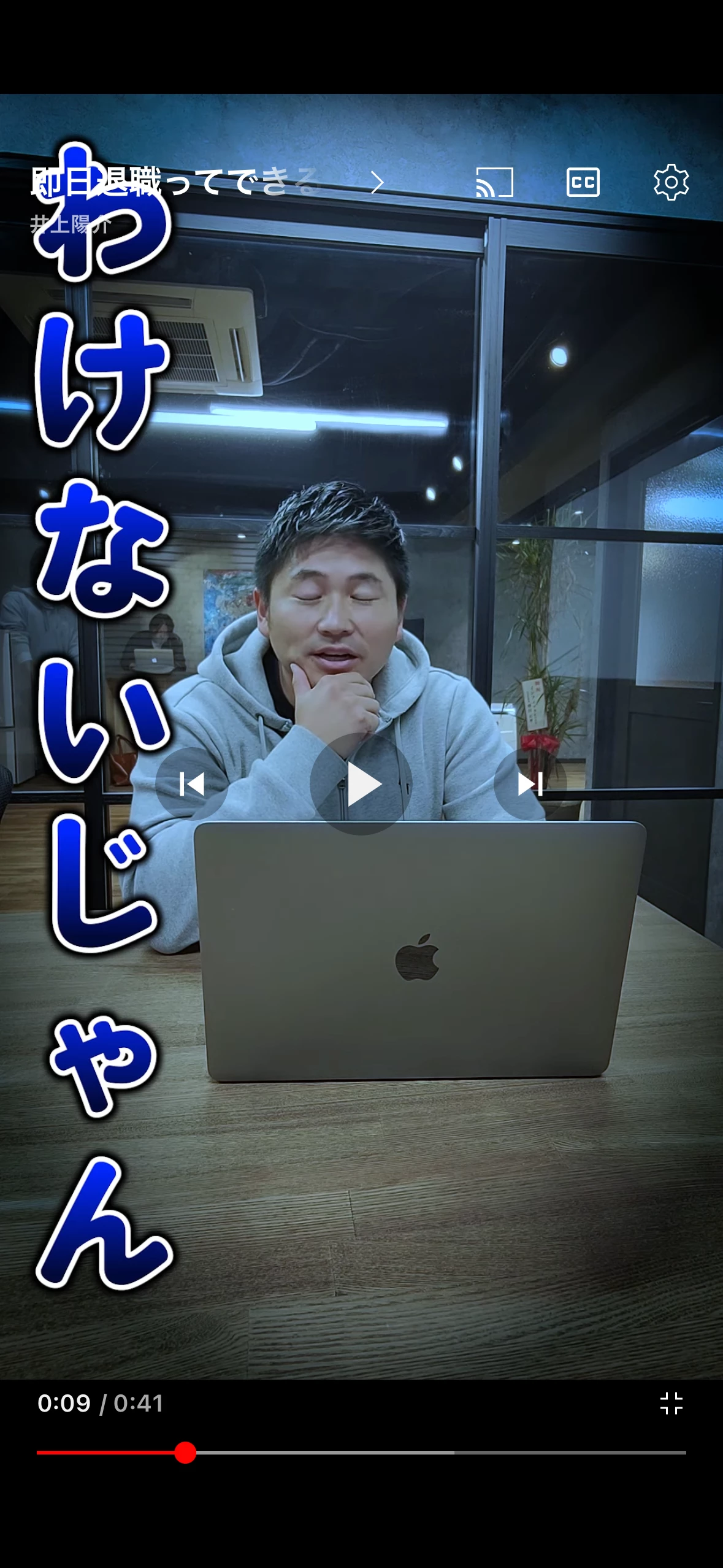
Photoshopの「マッチフォント」とか,Capture(モバイルアプリ)のフォントの画像検索を使えば,Adobe Fontsの中から探してくれますね。あとはAdobe Fontsサイト内で条件を変えたり絞ったりして目視ですかね。
それ以外だと,「Adobe」は関係なくなっちゃいますねぇ…。
「わけないじゃん」は,V7丸ゴシックかもです。
「Respon~」は,エルが曲がっているのでUD系ですかね。「源真ゴシック」なんかが雰囲気近いです。和欧別フォントかも?
「できる」は,「RoG2サンセリフStd」がまあまあ近いですけどこちらも「?」は別のフォントかも?
→ぉぉぉ。「コーポレート・ロゴ ver2 Bold」っすね!